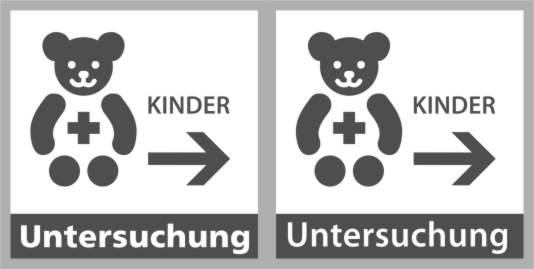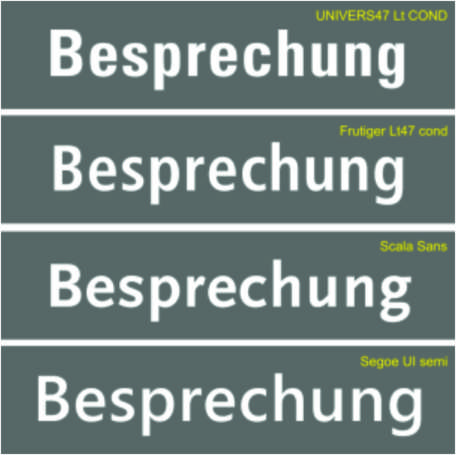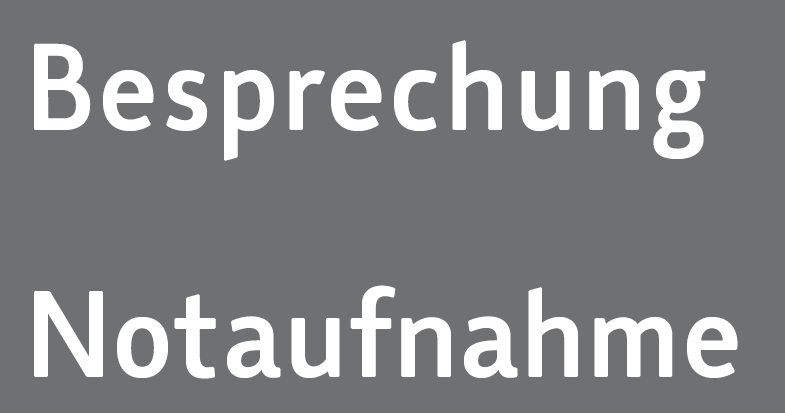
Schilder mit Piktogramm
Aufgabe ist ein "Auslegerschild" 150 x 150 mm mit Piktogramm und Bezeichnung zu erstellen.
Also z. B. Piktogramm in grau + Text grau "BESPRECHNUNG" (siehe Bild). Der Text steht in einem Balken mit 70% schwarz als weiße Schrift.
Habe derzeit eine UNIVERS CONDENSED LT47 light wegen der schmalen Laufweite bei langen Texten.
So richtig glücklich bin ich aber nicht damit.
Ich muss das Schild aus ca. 10-15 m zumindest gut erkennen können. Lesen dann vielleicht bei 7-10 m?
FF Info comes to mind ... Idealerweise solltest Du aber auf durchgehende Versalien verzichten – oder wenigstens S P E R R E N (und ausgleichen!), damit's halbwegs lesbar bleibt :D
Anbei noch ein paar Varianten mit Zeichenausgleich (spacing) und Groß-/Kleinbuchstaben
UNIVERS 47 lt Cond - Frutiger 47 LT Cond - Scala Sans und Segoe UI semi
Daher hab ich ja die FF Info ins Rennen geworfen – von Spiekermann fürs Leitsystem des Flughafens Düsseldorf entworfen ;)
Was sagt ihr zu "Aqua Rotis Sans Semi sans" und zum Thema DIN A3 quer und wieviele Zeilen maximal?
Ich werfe mal 9 Zeilen bei optimaler Schriftlesbarkeit ins Rennen..
Zur Agfa Rotis fällt mir nicht sehr viel mehr ein als »grusel«, vielleicht noch Otl ... ;) Zur Lesbarkeit ... Von einer A3-Seite im Querformat möchtest Du schon gerne mal einen, vielleicht zwei Schritte weit weg stehen, um überhaupt die ganze Seite erfassen zu können; wie weit willst Du weg sein können ...? Vermutlich nicht allzu weit, denn eine ausgesprochene Leitsystemschrift ist die Rotis nicht ... Zeilenabstand sollte auch nicht zu klein sein, zumal Du vermutlich hier nicht an einen durchgehenden Text denkst ... Arbeite doch versuchsweise mal mit einer A4-Seite (gut selbst auszudrucken) und halbierten Werten, was die Entfernungen angeht, und schau was die Rotis hergibt ... :?
Weiter oben schreibt der TO:
"Auslegerschild" 150 x 150 mm … und: … Ich muss das Schild aus ca. 10-15 m zumindest gut erkennen können. Lesen dann vielleicht bei 7-10 m?
Das könnte mit der Rotis schwierig werden … :?
ja, das habe ich mir nämlich gedacht. Das Otl-Prinzip ist nicht das "non + ultra". Weder "Rotis" noch Piktogramme.
Ich habe z.B. einen Ebenenwegweiser mit 4 Ebenen à DIN A3-Modulen, also 4 x A3 gegenüber von Aufzügen.
Man läuft also quasi darauf zu. Entfernung also 2-3 m vor den Schildern, weil Gesamthöhe der Übersicht 1600-1800 mm.
Und es ist halt so dass teilweise 7-10 Informationen =Zeilen drauf müssen..
Daher würde ich schon dazu tendieren, dass eine Condensed-Schrift z.B. Myriad Condensed auch dort relativ gut funktionieren wird..
Das Otl-Piktogramm-Prinzip ist in sofern auch schlecht, da die Lizensierung der Piktogramme ein finanziellen Aspekt beinhaltet. Und dem Patienten ist es egal, ob die Piktogramme vom Designer oder woher auch immer sind.. Es muss als Bildsprache funktionieren und ästhetisch aussehen.
Was nützt mir also ein Symbol, das keiner versteht? Daher auch die Kombi Symbol+Text.
Die Wandwegweisung mit A3 (an den Schildern stehe ich auch relativ nah dran 1-2 m oder laufe vorbei und muss nur mein Ziel mittels Pfeil bestätigt wissen ist nicht unbedingt das Problem zumal ich wichtige Ziele unterstützend mit Deckenabhänger kennzeichnen kann, die dann ca. 800 x 210 mm groß sind und nur EIN oder ZWEI Wörter innehaben.
Inhalte sind kurz und prägnant, sowohl auf Wegweisern als auch auf Übersichten z. B.
Kapelle
Soziale Dienste | Seelsorger
Gynäkologie u. Geburtshilfe
Kreißsäle/Entbindung
Gynäkologische Ambulanz
OP-Bereich | Aufwachräume
Chirurgie
WC Besucher
So sieht es in Wayfinding Sans in der mittleren Weite aus:
Gibt auch noch einen schmaleren Schnitt, aber dass Beschilderungen immer in Condensed sein müssen, ist auch in gewisser Weise ein Mythos. Im Idealfall wächst das Schild natürlich mit der Schrift mit. Wenn die Größe vorgegeben ist, kann es aber auch durchaus sein, dass eine breitere Schrift, die dann logischerweise kleiner wird, genauso gut oder besser lesbar ist, als eine Condensed, die zwar dann größer erscheint, aber durch ihre schmalen, gleichförmigen Formen wieder etwas verliert.
Hallo Ralf,
ich gebe dir völlig Recht, dass das Zusammenspiel Größe Schild-Schriftart-Leserlichkeit/Klarheit in Zusammenhang mit Schriftgröße + ZAB ein wesentlicher Aspekt ist.
Und die Klarheit der Wayfinding ist immer wieder faszinierend! Sehr gut!
Ich mache mal ein Schild komplett und poste das dann.
Danke übrigens Allen für den Austausch! :))
Hallo Ralf,
was mache ich denn nun mit deinem Hinweis? ;))
Ich muss die Schilder fertig stellen und die "WAYFINDER SANS" ist ja (noch nicht) käuflich erwerbbar...
Wie wäre es mit einer Art "Referenzanwendung", die dann entsprechend in Bezug auf die neue Schrift erwähnt werden kann?? Würde ich mit dem Kunden absprechen...
Calibri
Trebuchet MS
Bei der Trebuchet das "g" + "Q" nun gut. Das "e" zu kurzer Bogen-nicht unbedingt störend?!
Aber ich habe auch kein Wort mit"Q"..
Lesbarkeit auf langen Fluren in 2,10 m Höhe auf 10-15 m-da gehen mir die dünnen Schriften leicht unter.
Beim Laserdruck verschwimmen die Kanten auch wegen 70% schwarz. Für Digi-Offsetdruck muss ich Budget prüfen. Daher eher Tendenz zu etw. dickeren Schriften..
Tja Ralf-schade dass deine Schrift (noch) nicht verfügbar ist.. Das ist dann die Mischung aus allen.